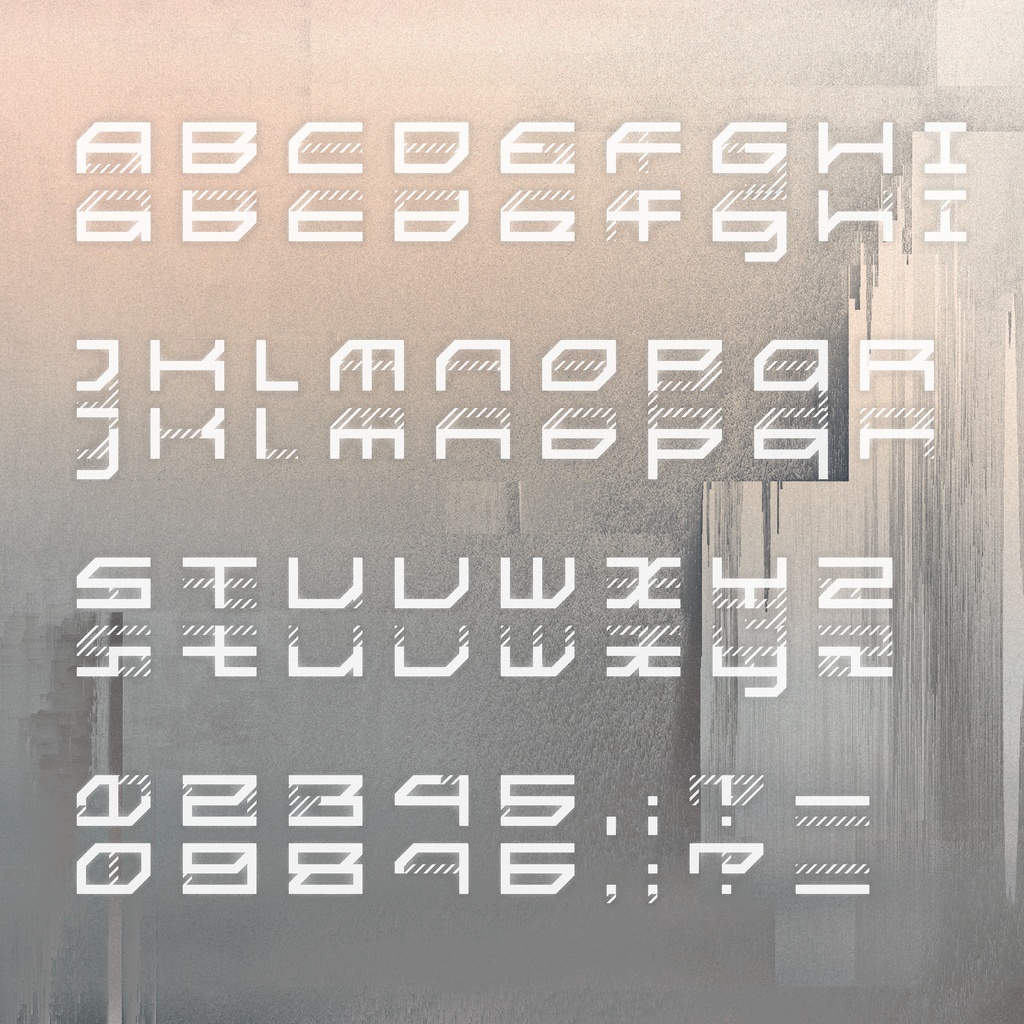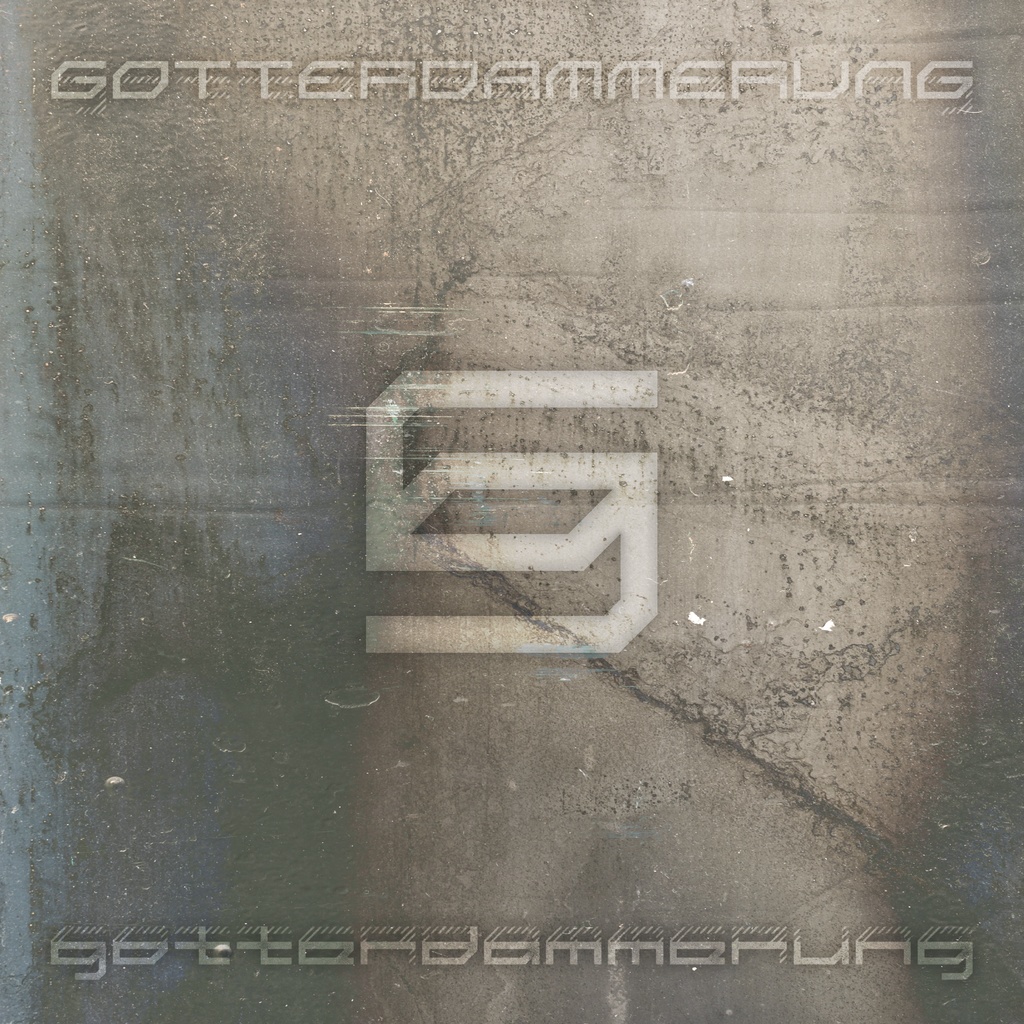
【無料フォント】Gotterdammerung 「無料」
🔁 Gotterdammerung 🔁 📢📢📢📢📢📢📢📢📢 特記事項 📢📢📢📢📢📢📢📢📢 リツイートで新フォントを配布する企画を開催中。 📢新しいフォントが掲示ツイートが目標達成から1ヶ月間のみ無料配布され、その後は有料となりますが。また、配布開始ツイートが毎回100RTの倍数を超えると、まだ1ヶ月間無料でDLできます。📢 ☕️価格設定には、集中力を維持するために、缶コーヒーに依存しているです。 そのため、大体の制作日数×日本での缶コーヒーの値段でフォントの価格を算出することにします。☕️ 📢📢📢📢📢📢📢📢📢 デザイン説明 📢📢📢📢📢📢📢📢📢 この作品を3日で完成予定。このフォントに過度な期待はしないで下さいね。 このフォントの発想は、人間が希少になり、AIや機械が無関心で効率的なスタイルで行動することに集中するようになると、同じ構造が2つの異なる文字を表現できるの幻想機械風フォントです。 📢📢📢📢📢📢📢📢📢 利用規約 📢📢📢📢📢📢📢📢📢 個人、商用どちらでも利用可能です。 ✨フォントが使用されたら、ツイッターにお知らせくださいhttps://twitter.com/amari_design✨ 本素材を使用した作品については、リツイートなどの形で宣伝させていただく場合があります。 フォントのインストール等の技術的なサポートはいたしません。使用して発生したと思われる如何なる問題についても、作者は責任を負わないものとします。 著作権を放棄することはありません。 商標を登録したり、作者であると主張したり、データ自体を販売または再販したりすることは禁じられています。 このコンテンツの最終的な解釈権は作者に帰属します。 内容補充とバージョン更新は製作続けるです。使用する際は最新バージョンにご注意ください。 📢📢📢📢📢📢📢📢📢 収録內容 📢📢📢📢📢📢📢📢📢 ラテン文字、数字、仮名だけてを含む295グリフが含まれています。 ーーーーーーーーーーーー Twitter:https://twitter.com/amari_design Behance:https://www.behance.net/9f45706b ーーーーーーーーーーーー